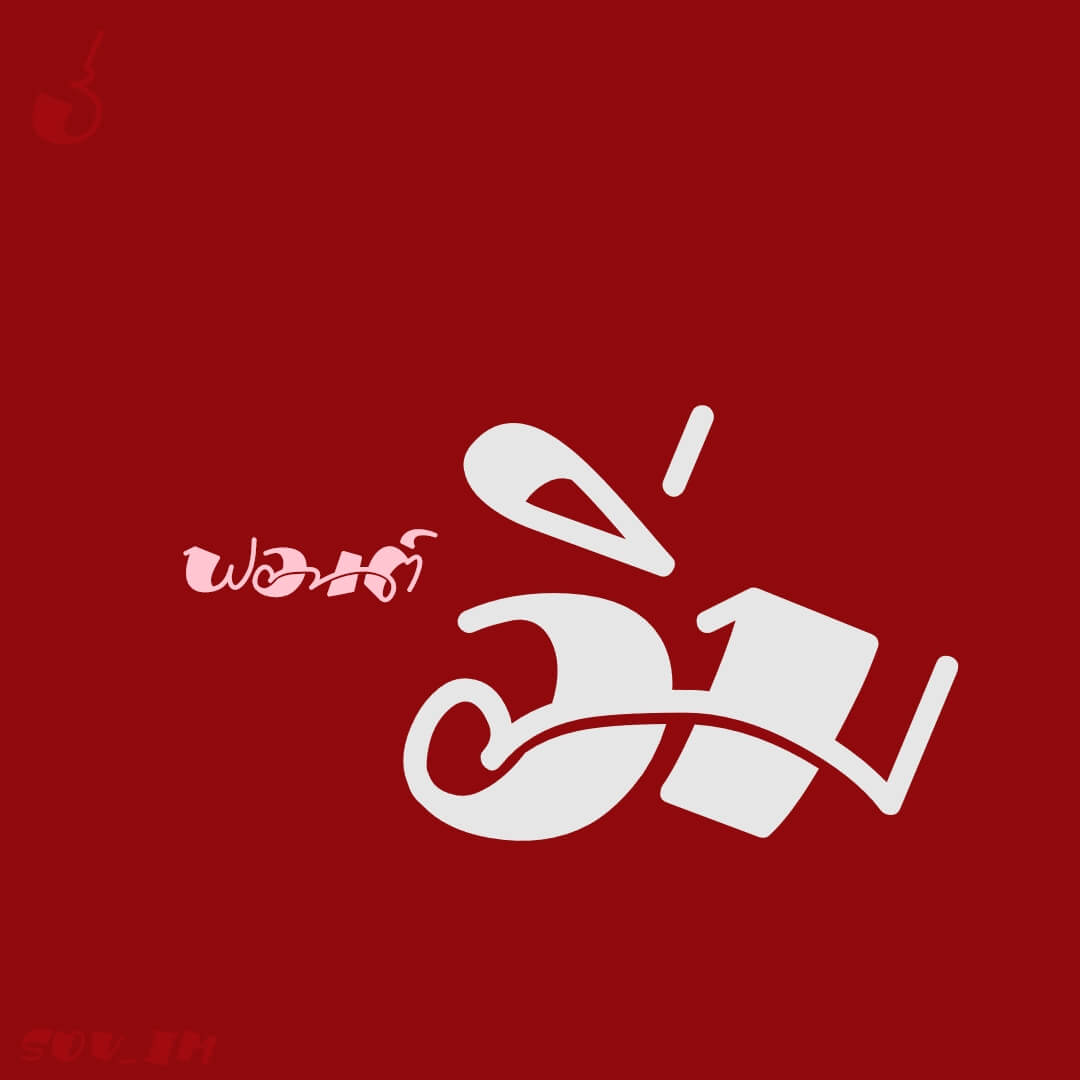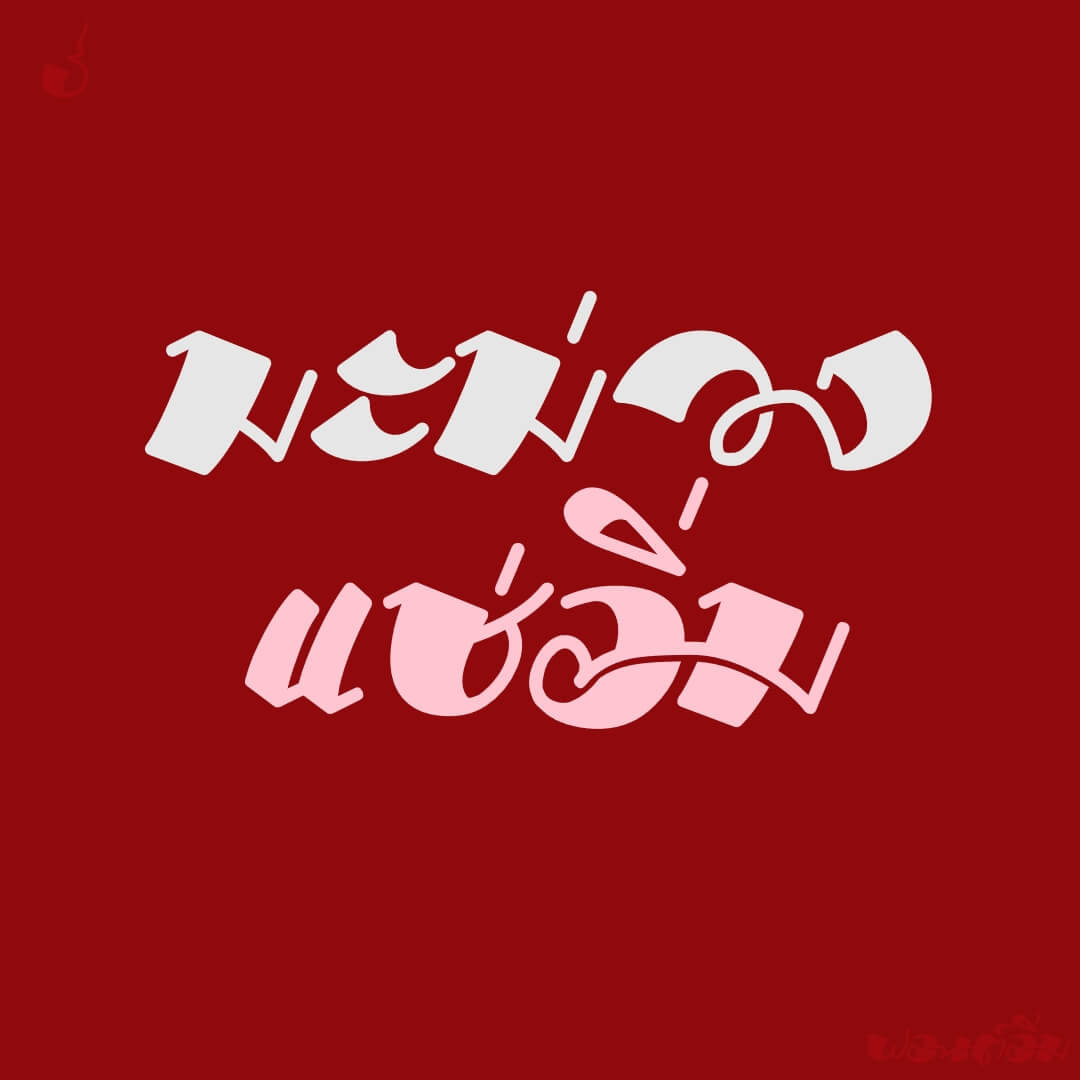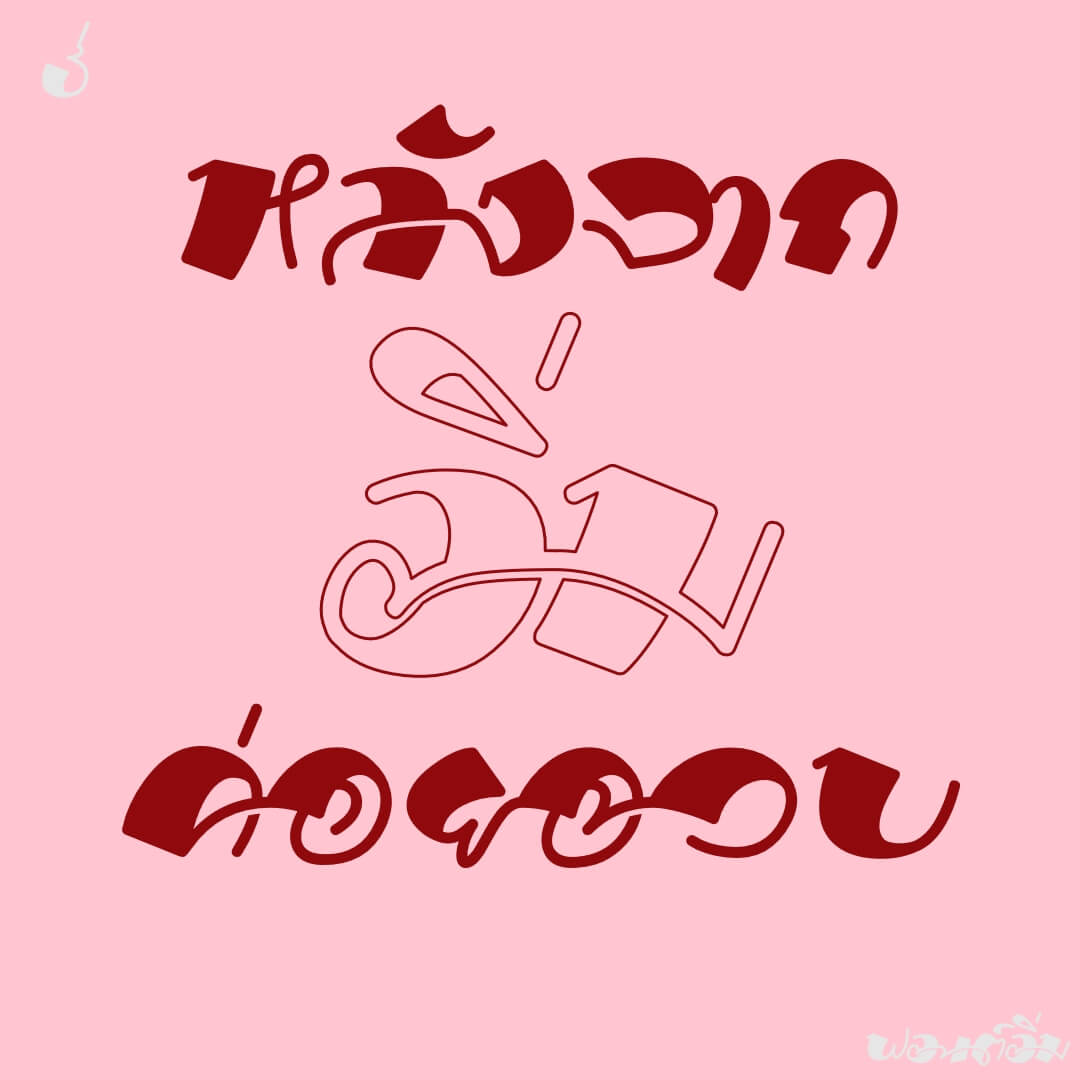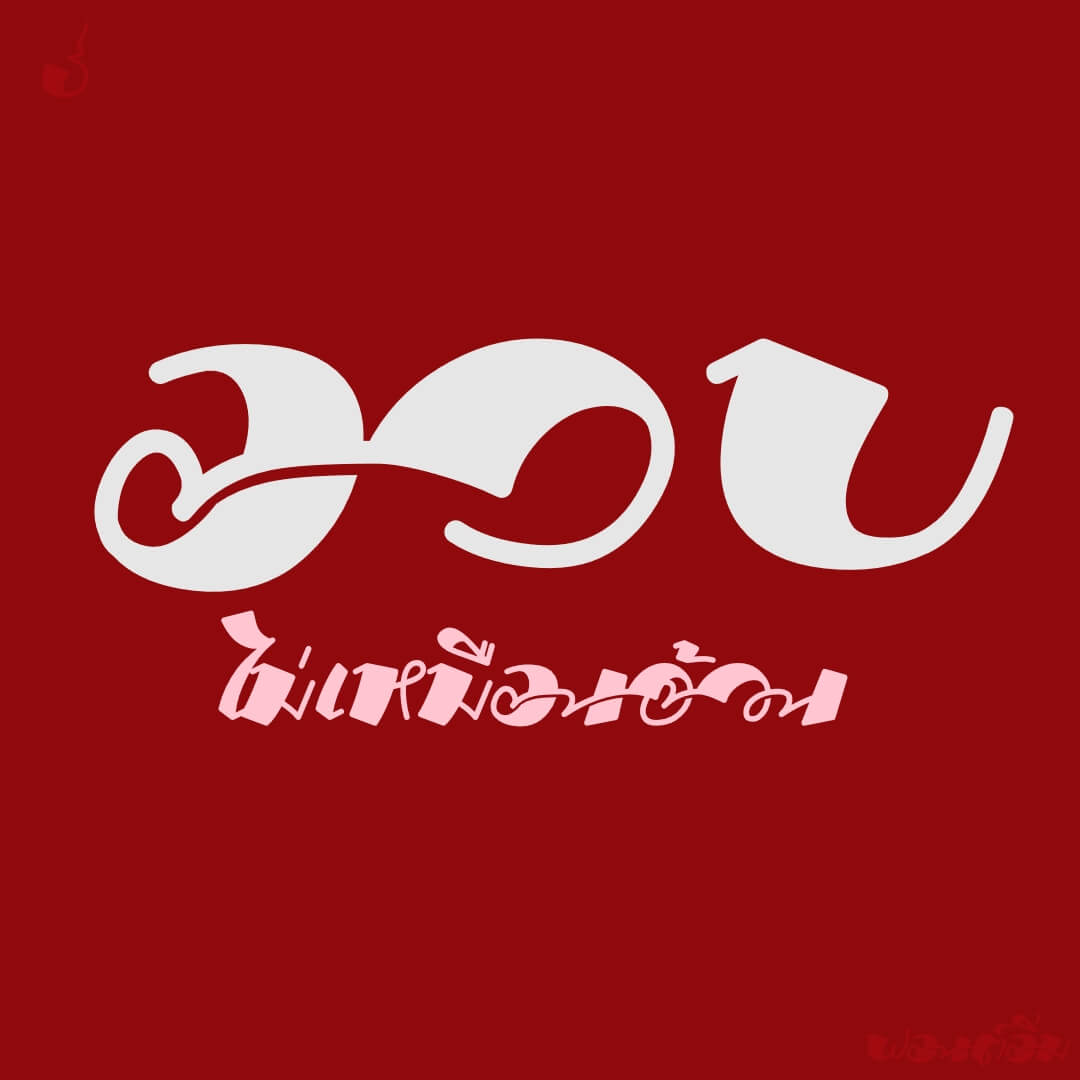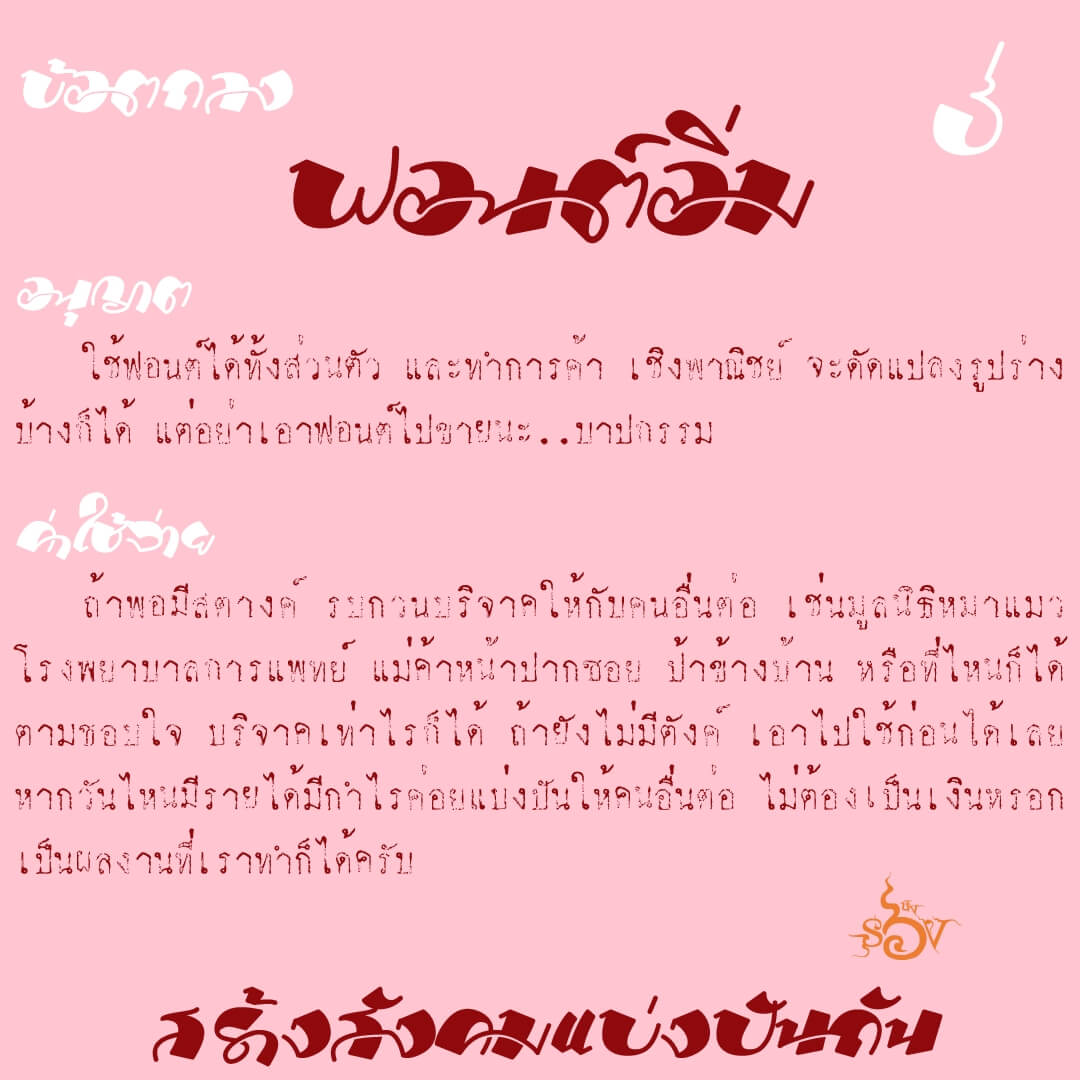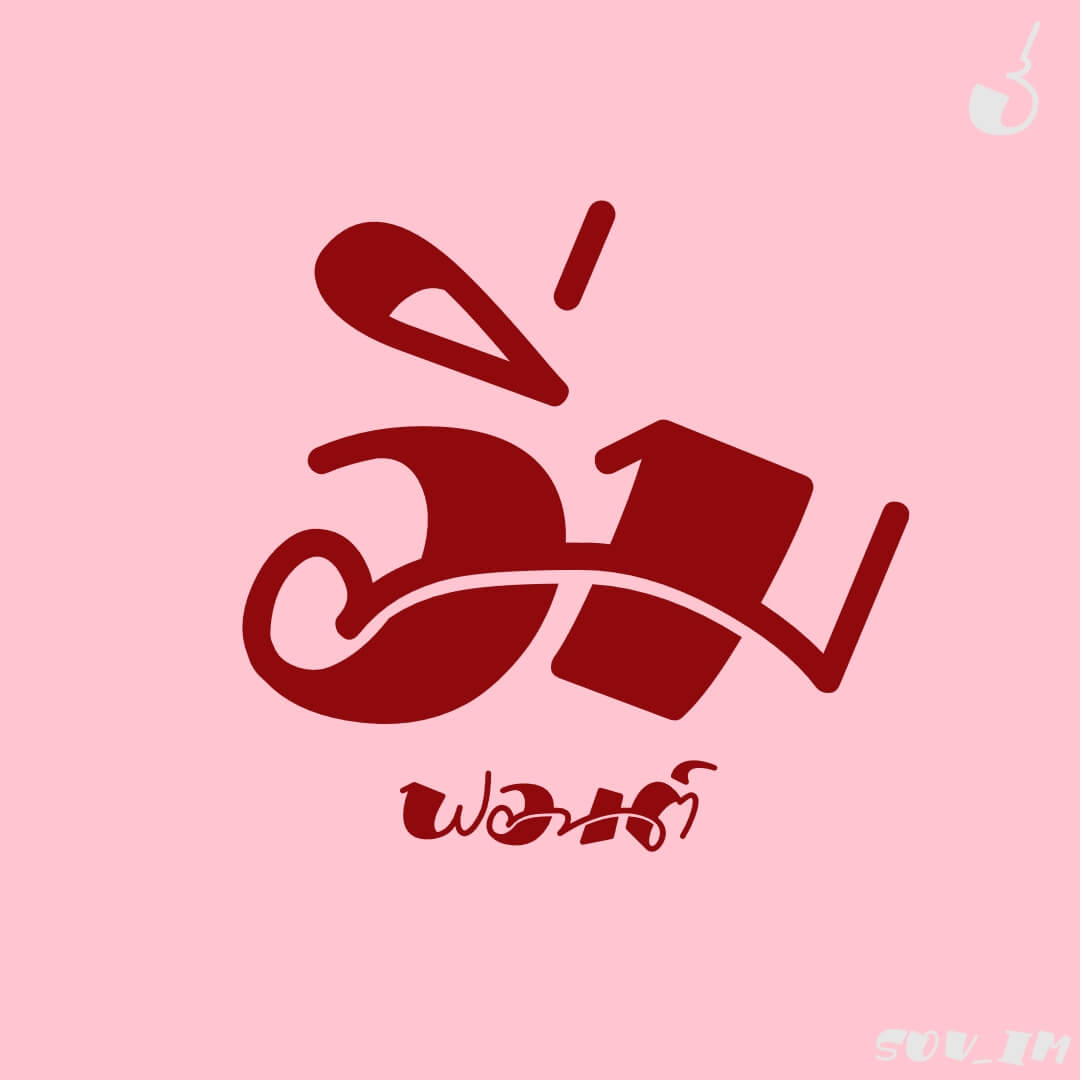
ฟอนต์อิ่ม เป็นฟอนต์แนว high contrast ที่มีเส้นหนามากกับเส้นบาง ผสมการเป็นฟอนต์ปากกาหัวตัดเส้นใหญ่ สามารถเขียนได้จริง เพิ่มการทำ pair letters จับคู่อักษรด้วยการเชื่อมเส้นบาง และตัดเส้น
เบื้องหลังการออกแบบ : ฟอนต์ อิ่ม
อิ่ม (SOV_Im)